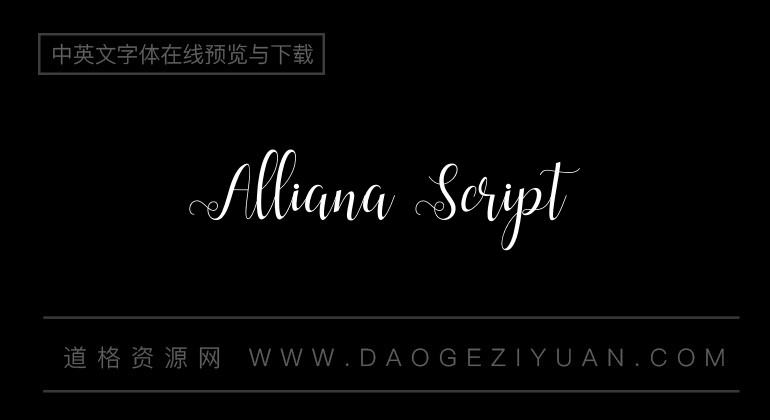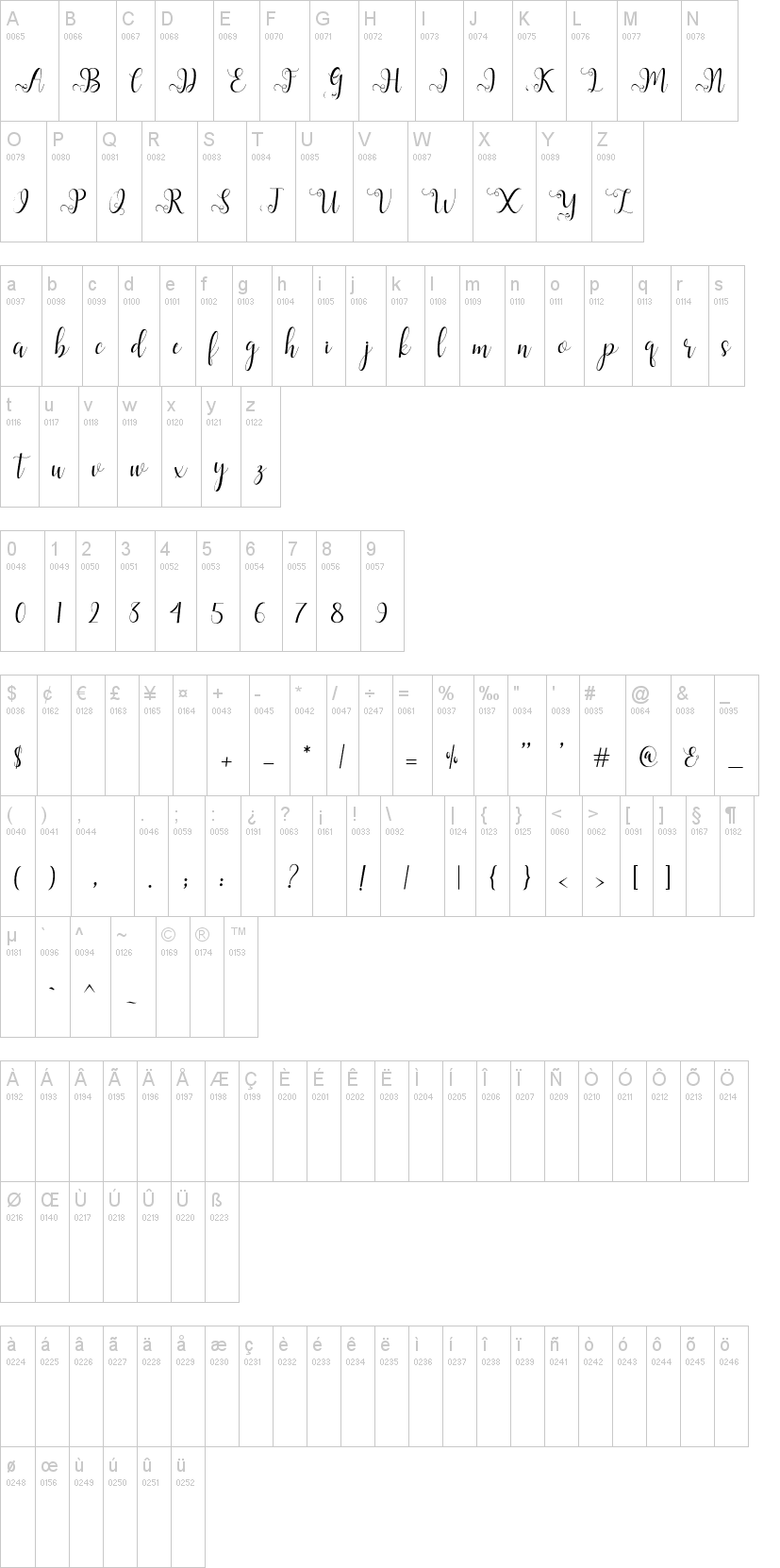
Alliana Script是一种华丽的手写笔画字体,具有流畅的曲线和优美的线条,适合用于各种设计项目,如品牌标志、海报、包装、名片、信件等。 该字体具有明显的手写风格,每个字母的笔画都经过精心设计并使用连字符连接,使得整个字体看起来非常自然和完整。此外,Alliana Script还提供了各种替代字形和连字符,可以帮助设计师在自己的作品中增加更多的个性和创意。 Alliana Script提供了多种不同的字重和字体风格,包括常规、粗体、斜体等等。它还支持多种语言,包括英语、法语、西班牙语、德语等等。 总的来说,Alliana Script是一种非常优美和多功能的手写字体,适合用于各种设计项目,特别是那些需要突出品牌个性和创意的项目。内容介绍
Alliana Script是一款非常不错的手写艺术字体,具有很好的视觉感,适合于文化类的宣传设计、商业类品牌的广告和产品包装设计以及个性化文字排版等较多场景。